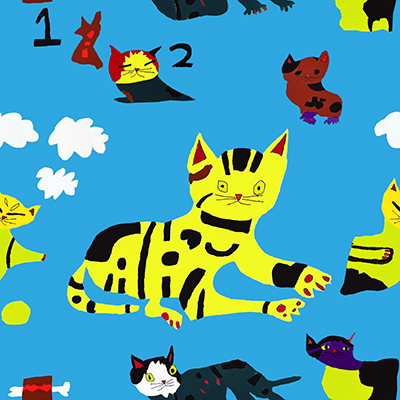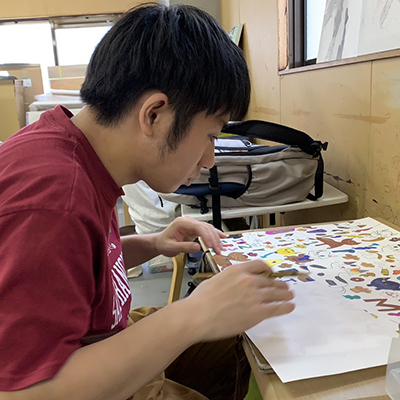
ねこの世界
Artist吉川豪起
Designer池田充里
Organizationアトリエライプハウス
豪起のネコがみんなに愛されることを願っています。(母 美佐緒さん)(吉川豪起)
個性のあるキャラクターの猫がいっぱい!あなたの推しネコは見つかりましたか?(池田充里)
吉川豪起さんは、かわいい猫たちをモチーフに絵画を描いています。彼の描く猫たち、一匹一匹に模様の違いや色彩に個性があります。描かれた猫たちに、作者の人柄が表れているように思います。(アトリエライプハウス)